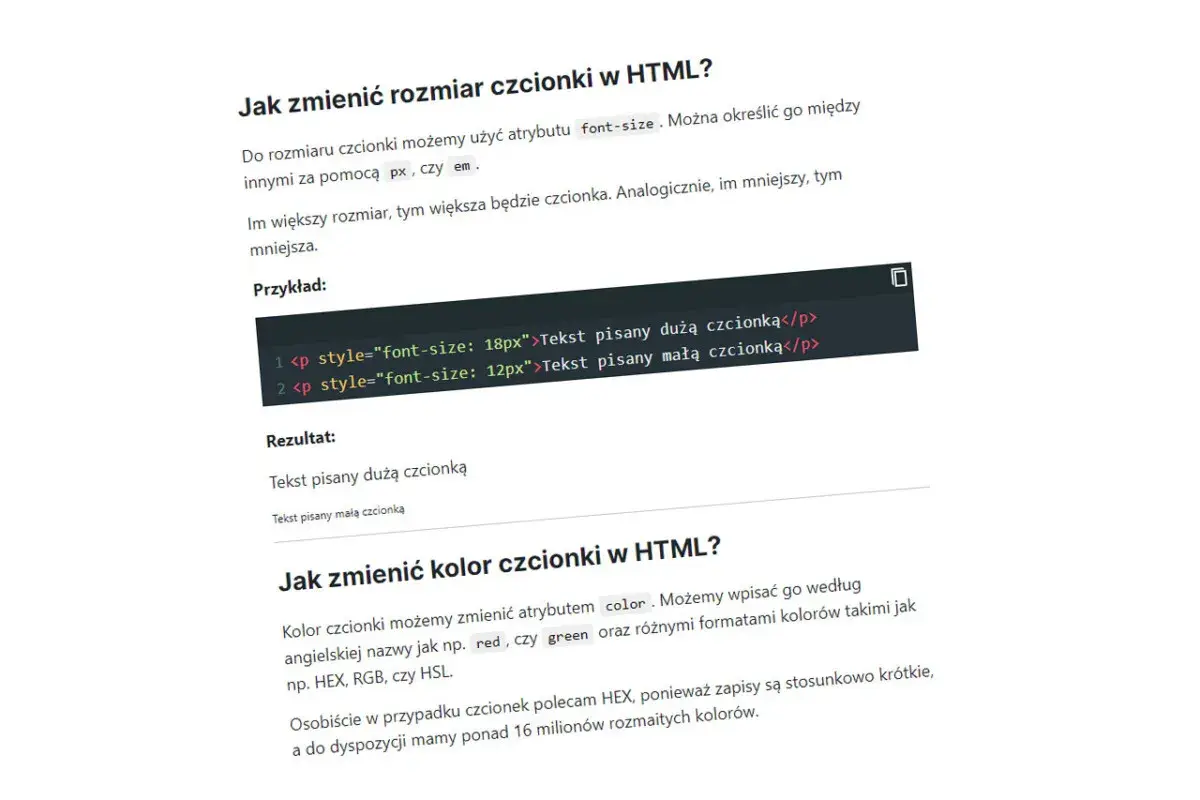
W typografii liczba „12 pt” wygląda prosto, ale w praktyce decyduje o niej kilka warstw: jednostka punktowa, konstrukcja kroju, interlinia i odległość czytania. Rozmiar czcionki w rzeczywistości bywa więc czymś innym niż podgląd w programie, zwłaszcza gdy przygotowuję ulotkę, menu, wizytówkę albo plakat dla lokalnej firmy. W tym tekście wyjaśniam, co naprawdę oznacza punkt typograficzny, ile to jest w milimetrach i jak dobrać wielkość tekstu tak, żeby po wydruku nadal był czytelny.
Najkrócej: punkt typograficzny, widoczność i odległość czytania
- Punkt typograficzny to jednostka projektowa, a nie wysokość widocznych liter.
- W druku 1 pt oznacza około 0,353 mm, więc 12 pt to nie 12 mm, tylko około 4,23 mm em square.
- Dwa kroje o tym samym rozmiarze mogą wyglądać inaczej, bo różnią się wysokością x, grubością i proporcjami.
- Na ekranie łatwo pomylić podgląd z realnym wydrukiem, dlatego test 1:1 jest najpewniejszy.
- Przy materiałach marketingowych sam rozmiar nie wystarcza, bo równie ważne są kontrast, interlinia i dystans czytania.
Co naprawdę oznacza punkt typograficzny
W praktyce punkt typograficzny jest jednostką, która opisuje skalę kroju pisma, a nie fizyczną wysokość litery na papierze. To ważne rozróżnienie, bo wiele osób zakłada, że „10 pt” znaczy po prostu „literki mają 10 punktów wysokości”. Tak nie działa typografia. Rozmiar w punktach odnosi się do umownego pola, na którym budowany jest krój, a nie do samego kształtu znaków.
W nowoczesnym składzie najczęściej spotkasz punkt PostScriptowy, czyli jednostkę zbliżoną do 1/72 cala. Dla projektanta oznacza to tyle, że numer w polu rozmiaru jest punktem odniesienia, ale nie daje pełnej odpowiedzi, jak duży będzie tekst po wydruku. Na ten sam zapis wpływają jeszcze wysokość małych liter, długość wydłużeń nad i pod linią bazową oraz ogólny charakter fontu.
Ja zwykle tłumaczę to w prosty sposób: pt mówi, jak font ma być skalowany, ale nie mówi wprost, jak wysoka będzie każda litera. Dlatego dwa różne kroje ustawione na 12 pt mogą wyglądać jak tekst o zupełnie innej wielkości. Za chwilę rozbiję to na liczby, bo właśnie wtedy najlepiej widać różnicę między teorią a praktyką.
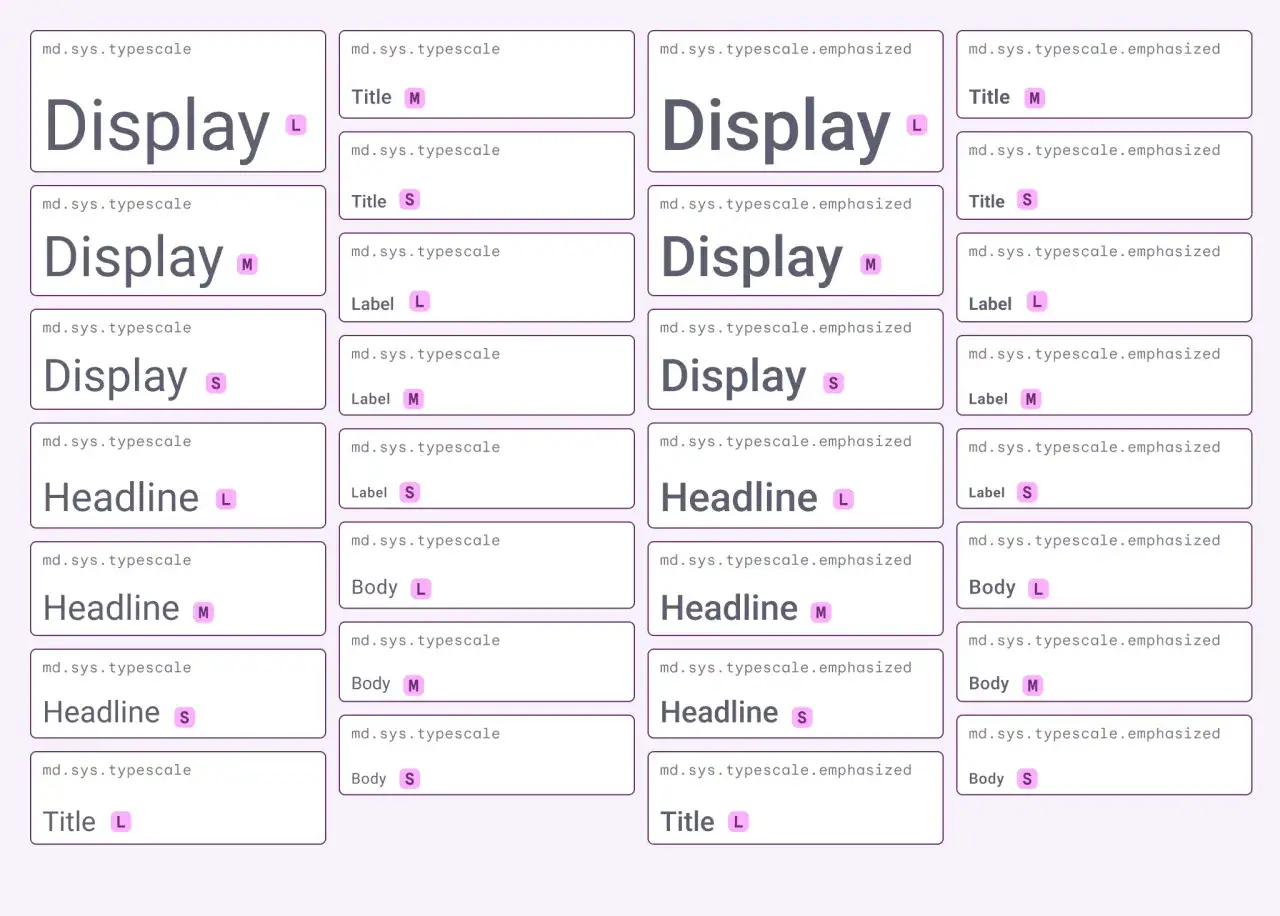
Ile to jest w milimetrach i calach
Jeśli chcesz szybko przeliczyć punkt typograficzny na fizyczny wymiar, najważniejsza jest jedna wartość: 1 pt to około 0,353 mm. To oznacza, że skala punktowa wcale nie jest duża, a rozmiary wyglądające na ekranie skromnie potrafią po wydruku być zaskakująco małe. Poniższa tabela pomaga to osadzić w realnych wymiarach.
| Rozmiar | Przybliżenie w mm | Praktyczne znaczenie |
|---|---|---|
| 6 pt | 2,12 mm | Bardzo drobne przypisy, raczej nie tekst główny |
| 8 pt | 2,82 mm | Małe stopki, informacje pomocnicze, etykiety |
| 9 pt | 3,17 mm | Minimum, które często sprawdza się w małych materiałach drukowanych |
| 10 pt | 3,53 mm | Bezpieczny punkt startowy dla krótkich akapitów |
| 12 pt | 4,23 mm | Komfortowy rozmiar w wielu materiałach do czytania z ręki |
| 14 pt | 4,94 mm | Dobrze działa przy nagłówkach i krótszych blokach treści |
| 18 pt | 6,35 mm | Wyraźne śródtytuły i hasła widoczne z większej odległości |
| 24 pt | 8,47 mm | Mocne nagłówki, plakaty, elementy ekspozycyjne |
Ta tabela jest przydatna, ale nie wolno traktować jej jak sztywnej normy. Papier, drukarka, rodzaj pliku, raster i sposób eksportu potrafią dać drobne różnice. W materiałach reklamowych traktuję więc te wartości jako punkt wyjścia, a nie ostatnie słowo.
Sam przelicznik nie kończy tematu, bo dwa kroje o tej samej liczbie punktów mogą wyglądać bardzo różnie. I właśnie tu zaczyna się najbardziej praktyczna część całego zagadnienia.
Dlaczego dwa kroje 12 pt wyglądają inaczej
To jedna z najczęstszych niespodzianek w projektowaniu. Tekst ustawiony na 12 pt może wyglądać „większy” albo „mniejszy” tylko dlatego, że font ma inną budowę wewnętrzną. Liczy się nie tylko rozmiar, ale też proporcje, światło i ciężar liter.
Wysokość x robi największą różnicę
Wysokość x to odległość między linią bazową a górną granicą małych liter, takich jak „x”, „a” czy „e”. Krój z wyższą wysokością x zwykle wygląda na większy i czytelniejszy przy tym samym ustawieniu pt. Dlatego prosty grotesk często sprawia wrażenie „większego” niż bardziej elegancki szeryfowy krój, choć liczba w panelu jest identyczna.
Grubość i szerokość zmieniają optyczny ciężar
Cienki font w małym rozmiarze traci wyrazistość szybciej niż kroj o stabilniejszym rysunku. Z kolei krój szeroki albo bardzo rozstrzelony zajmuje więcej miejsca i szybciej rozbija układ. W praktyce oznacza to, że rozmiar i styl trzeba oceniać razem, a nie osobno.
Kapitały, wydłużenia i interlinia wpływają na całą kompozycję
Wysokie wersaliki, długie wydłużenia w górę i w dół oraz zbyt ciasna interlinia potrafią sprawić, że tekst wygląda ciężej, niż sugeruje sam zapis. W druku tekst podstawowy często czyta się wygodniej przy interlinii na poziomie około 120-140% wielkości pisma. To nie jest magiczna reguła, ale dobry punkt startu dla ulotek, katalogów i menu.
- Wybierz krój o dobrej czytelności, nie tylko ładny wizualnie.
- Dopasuj rozmiar do nośnika, a nie do przyzwyczajenia z ekranu.
- Sprawdź kontrast i interlinię, zanim uznasz projekt za gotowy.
- Zawsze zrób wydruk próbny 1:1, jeśli materiał ma trafić do druku.
Właśnie tak najlepiej odczytuje się rozmiar czcionki w rzeczywistości: nie z samego numeru w programie, tylko z tego, czy tekst da się przeczytać bez wysiłku, w konkretnym miejscu i z realnej odległości. Jeśli ten warunek jest spełniony, typografia zaczyna pracować na korzyść marki, a nie przeciwko niej.